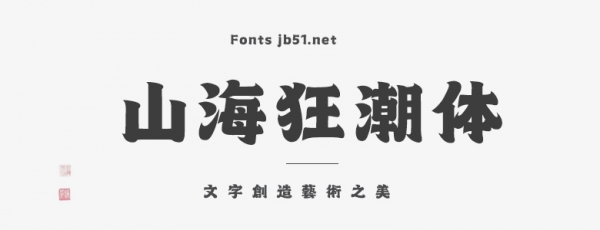
山??癯斌w是山海字庫發(fā)布的一款字體,字符集包含簡繁9169字。這款字體以其獨(dú)特的風(fēng)格和豐富的字符集,為用戶提供了豐富的文字選擇和設(shè)計(jì)空間。
山海狂潮體的設(shè)計(jì)靈感來源于中國古典文化中的山海經(jīng),融合了傳統(tǒng)與現(xiàn)代的設(shè)計(jì)元素,展現(xiàn)出一種獨(dú)特的視覺效果。其字符集包含了簡體和繁體中文,適合用于各種需要豐富文字表達(dá)的設(shè)計(jì)場景,如廣告、印刷、媒體、創(chuàng)意、動漫、攝影等領(lǐng)域